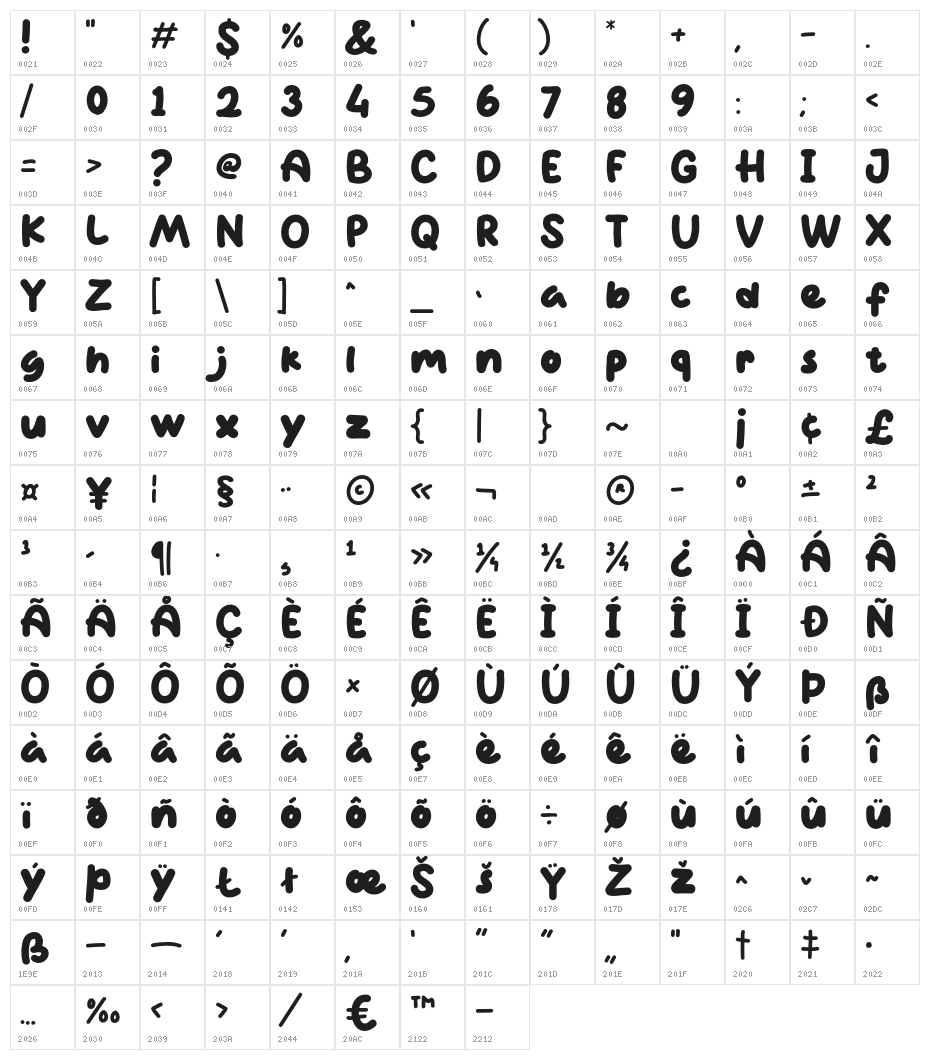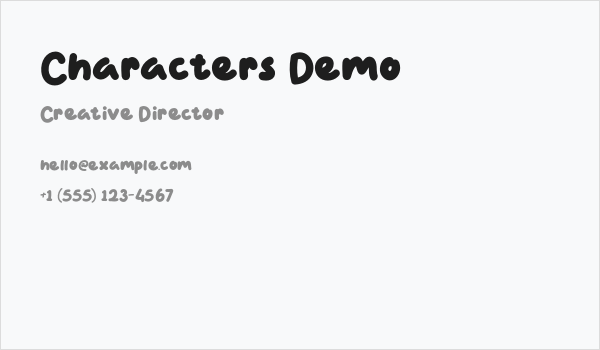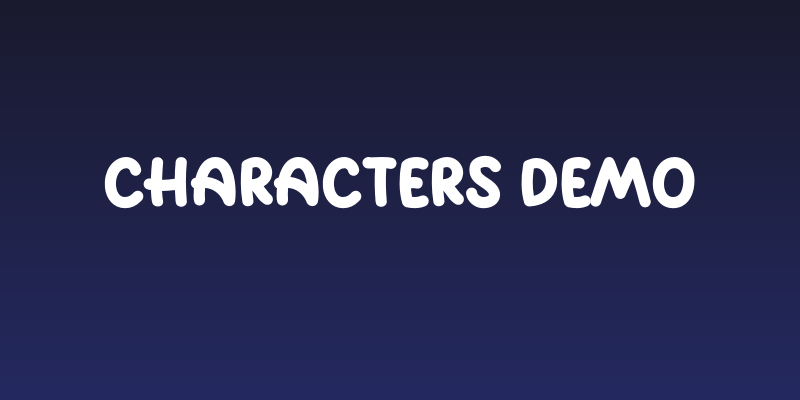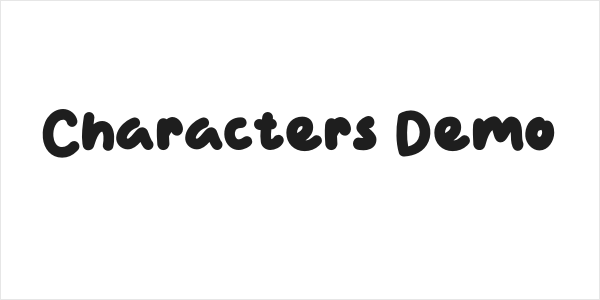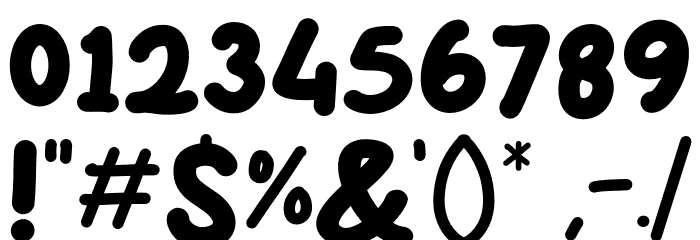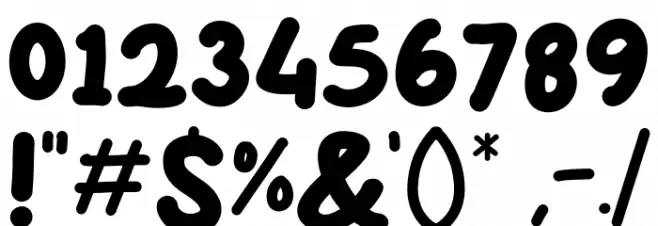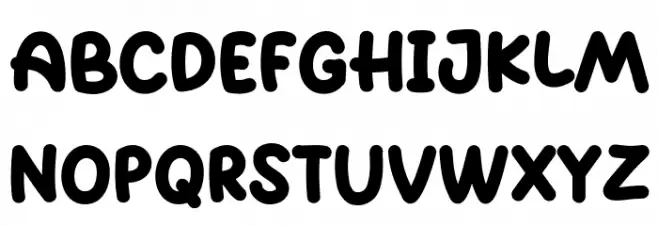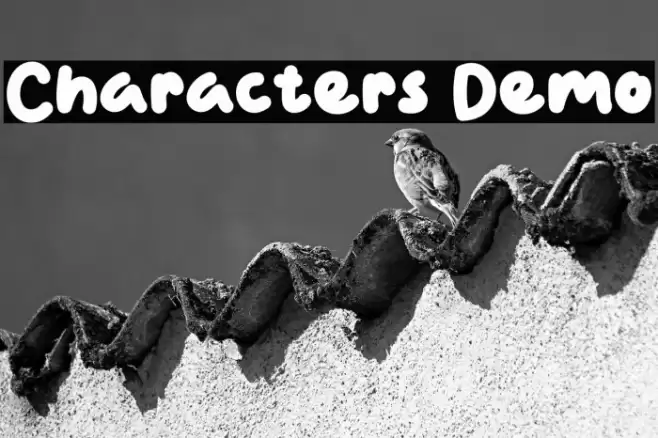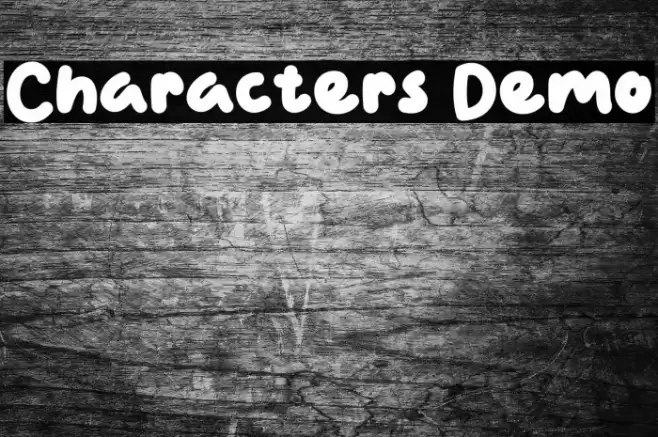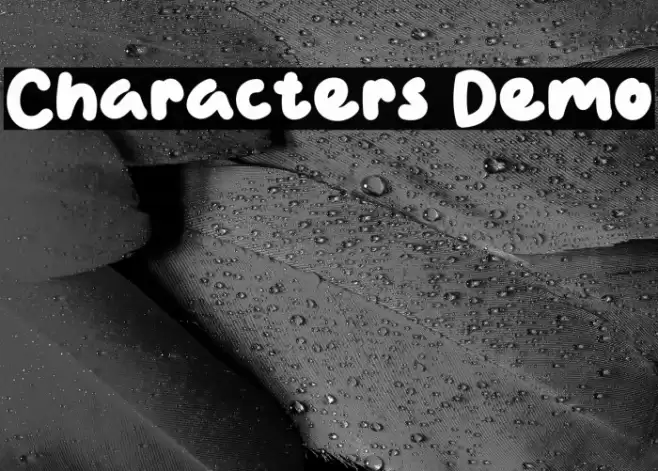
Characters Demo Font
| Gesamtstil | Playful |
| Vorgeschlagene Projekte | Ideal for children's books, playful branding, posters, and social media graphics. |